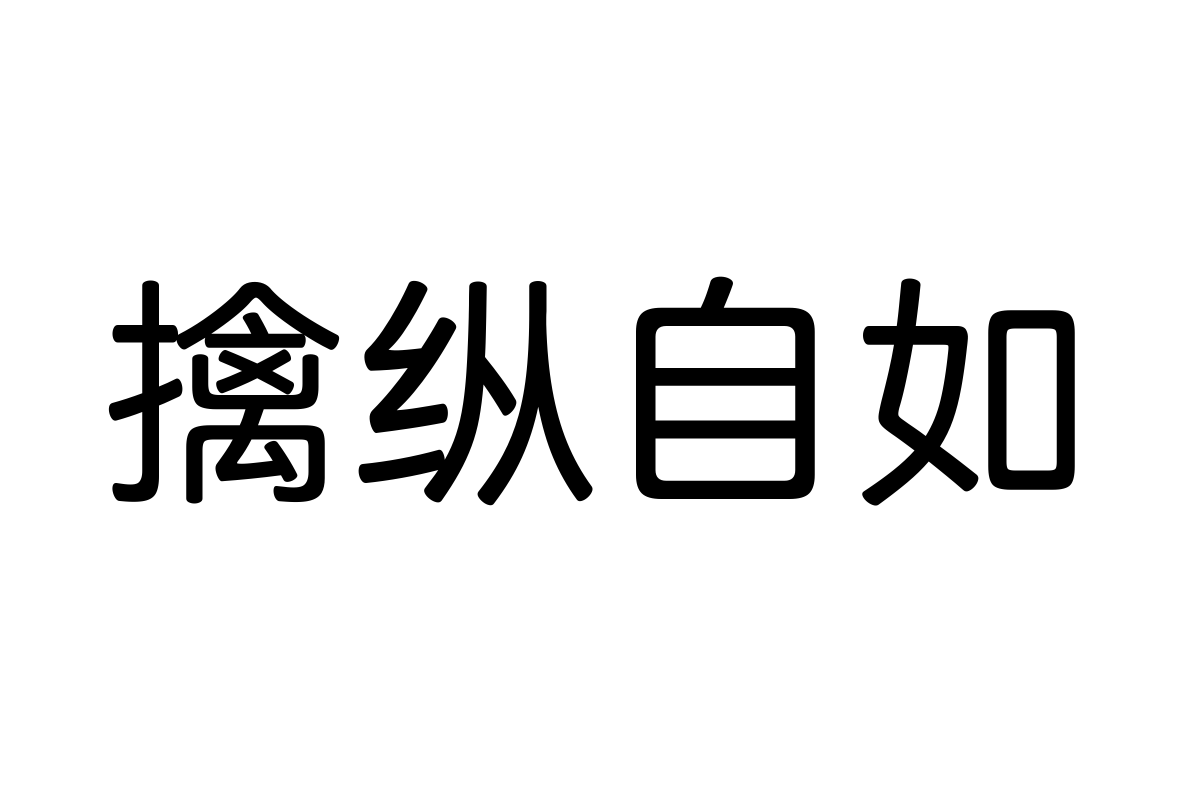
汉仪正圆-55字体是一款专为中文排版设计的简体字字体,具有简洁而统一的笔画结构,适用于多种设计场景。以下是对该字体的具体介绍:
1. **字符数量**:该字体拥有8089个字符,覆盖了从基本拉丁文到中日韩符号等广泛的字符类型。这种广泛的字符支持使得该字体在需要使用多种语言或符号的场合下尤为有用。
2. **字符分布**:汉仪正圆-55字体的字符分布非常广泛,包括拉丁文、希腊文、西里尔文等国际常用文字以及货币符号、数字形式等专业符号。这种多样化的字符集能够满足不同领域和行业的需求。
3. **风格特点**:该字体的风格为简体,被称为“55简”,意味着其笔画结构较为简单,易于辨识和使用。同时,它的整体笔画结构整齐划一,这有助于提升文本的整体视觉效果和阅读体验。
4. **适用领域**:由于其良好的辨识度和广泛的适用性,汉仪正圆-55字体非常适合用于文章编辑、海报设计等领域。无论是商业文档还是学术作品,这款字体都能提供清晰且专业的视觉表现。
总的来说,汉仪正圆-55字体以其丰富的字符集、统一的风格和广泛的应用范围,成为了一款实用的中文简体字字体。无论是个人用户还是专业设计师,都可以通过这款字体来提升自己的设计和排版能力。